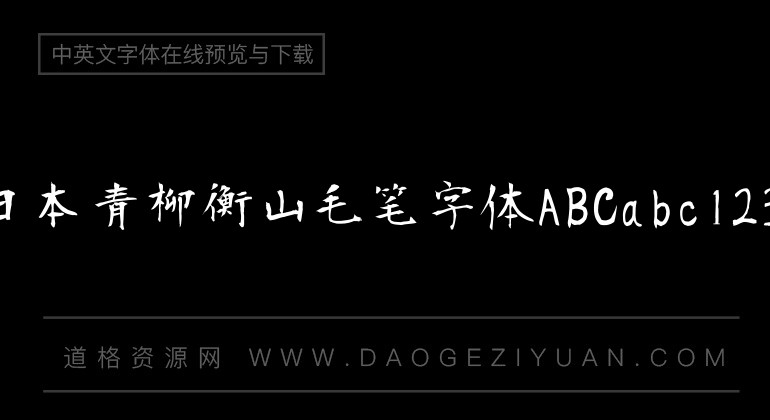
日本青柳衡山毛笔字体是一种独特的日本毛笔字体,在日本书法中具有很高的地位。这种字体源于日本著名的书法家青柳衡山先生,他在书法创作中将传统的中国毛笔书法风格与日本本土书法技法相融合,形成了这种具有日本特色的毛笔字体。这种字体的特点是线条流畅,笔画清晰,具有一定的装饰性,同时也非常注重笔画的节奏和节奏的变化,使得整个字体生动有力,给人以美感和艺术的享受。日本青柳衡山毛笔字体在日本书法和设计领域都被广泛应用,无论是书法作品还是广告设计、包装设计等,都能看到这种独特的字体的身影。文件名:日本青柳衡山毛笔字体
日本青柳衡山毛笔字体是一款非常不错的手写艺术字体,具有很好的视觉感,适合于文化类的宣传设计、商业类品牌的广告和产品包装设计以及个性化文字排版等较多场景。